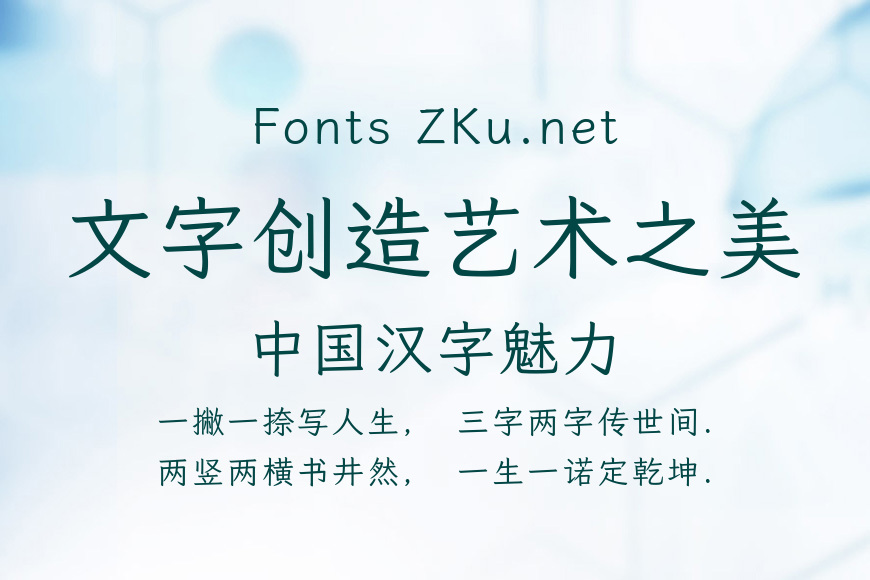
字体名称: 霞鹜文楷
霞鹜文楷
霞鹜文楷介绍
有着日本教科书体的写法,兼有仿宋和楷体的特点,可读性高。一些DIY字体爱好者曾先后用仿宋、刻本仿宋、仓耳今楷补全这款字体,做为手机系统的美化字体移稙在 iOS、Android 等手机系统中,受到很多机友的欢迎。不过这样补全的字体有一些不足之处。
第一,原有字体和后补字体之间有着一定的差异,致使一些不同的文字(如Klee原有汉字与后补简体字)混排之后会有违和感。
第二,由于补字所用的字体(如刻本仿宋、仓耳今楷等)为商业版权字体,补全之后不可用于商业用途,还会有侵权的风险。
鉴于此,本人开始了为Klee这一高质量的日文字体补全简体字的尝试。补全后的字体拟命名 「霞鹜文楷」。选取原字体 SemiBold 字重做为Regular字重。
霞鹜文楷字体LXGWWenKai字库是一款让人赏心悦目、百看不厌的中文字体,适合各类广告和产品包装设计应用,字体大小8.62MB,格式为ttf字体,上传用户是手机洗相,作者/版权方为落霞孤鹜